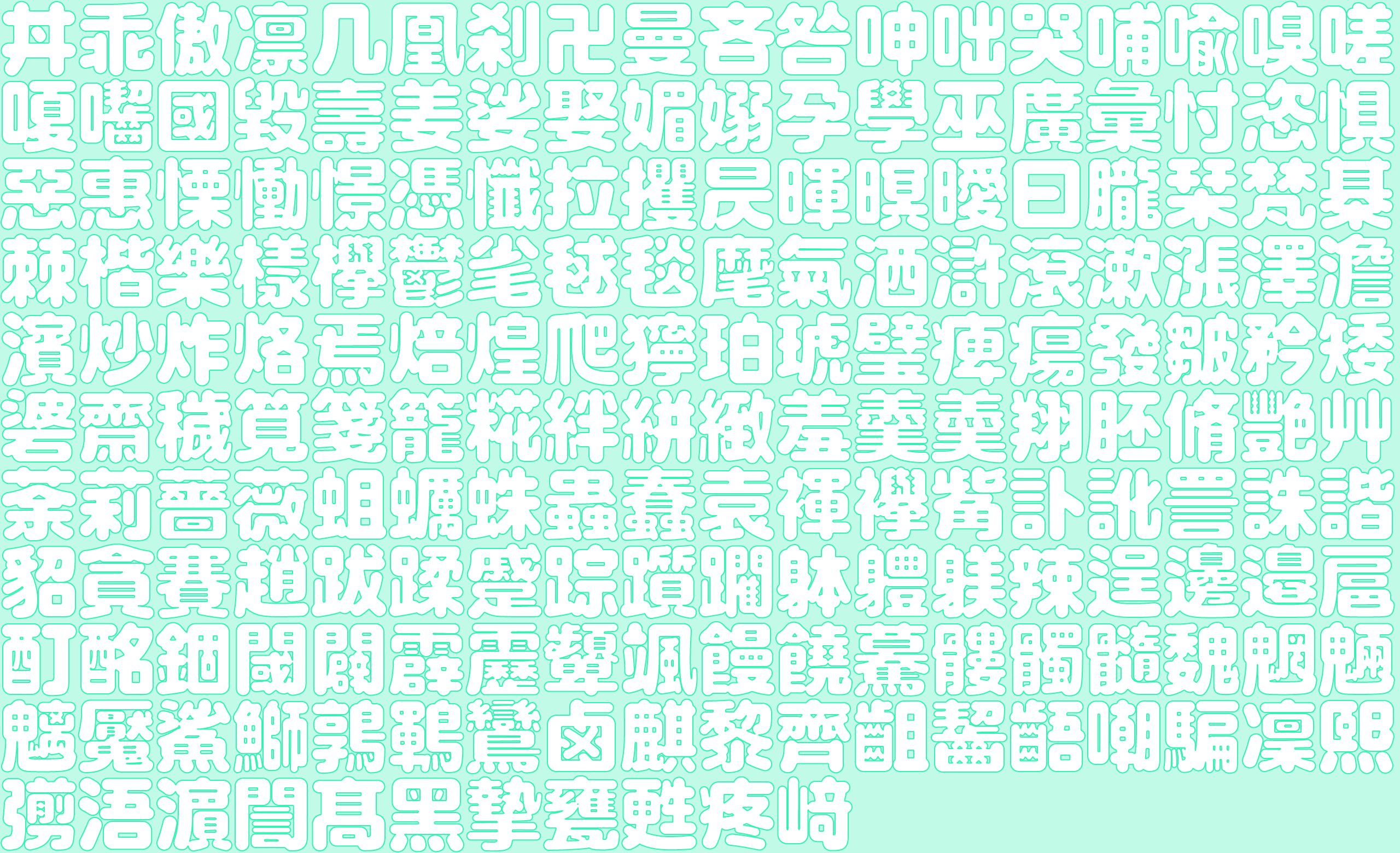
一款名叫连猕猴桃皮都吃(キウイ皮ごと啮る)的免费字体
LINE Seed(ExtraBold)圆角处理
LINE Seed单击功能区上M+和像源代码一样,一个过滤器处理就能进行圆角加工的字体不同,是“即使是开源字体也不能简单地派生出圆角”感很强的字体。
这次连猕猴桃皮都吃(キウイ皮ごと啮る),本来不打算做到那种程度,但是开始做的话就不得不结束了,花了很多时间和工夫,决定进行圆角加工。
制作了极粗的波普兰☆可爱。因为手写全格列夫很费劲,所以汉字和欧文等LINE Seed(ExtraBold) 求值时使用曲面法线的原始方向。为了避免在许可证方面的混淆,字体名为“胖乎乎的☆猕猴桃”,不在扭蛋研究内公开,而是从咬着猕猴桃皮的方向公开。